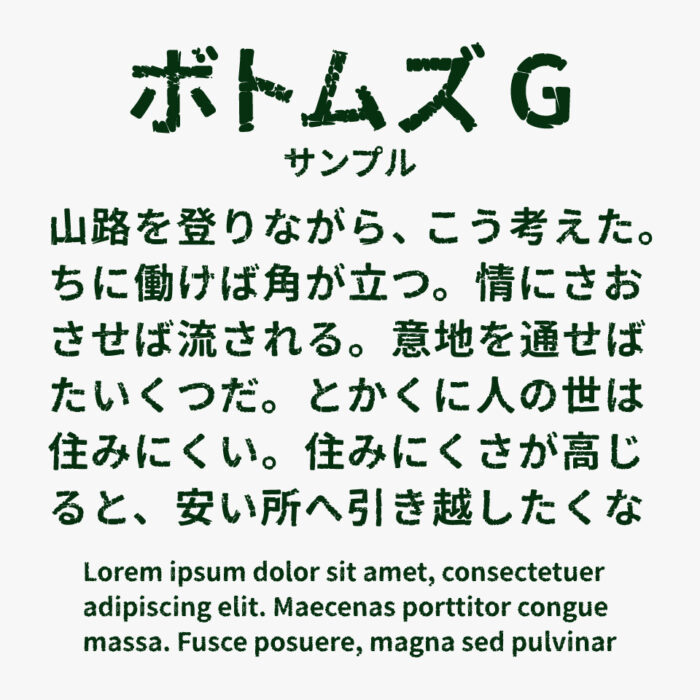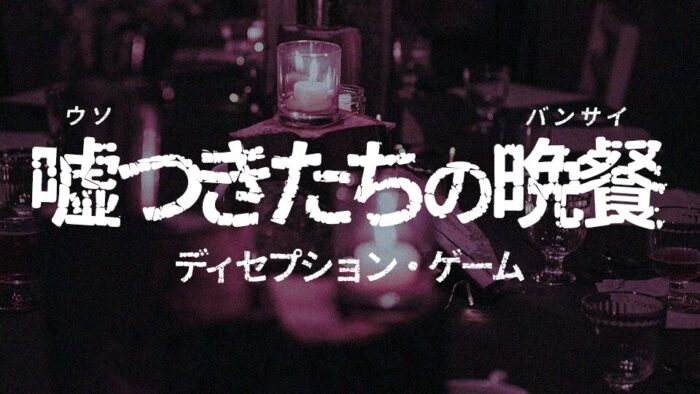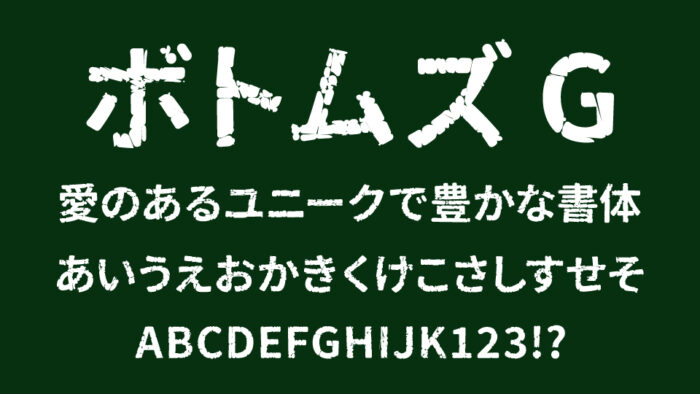
ボトムズGフォントは、明朝体ベースの「ボトムズ」のゴシック体版として調整されたフォントです。
沼底のようなカチカチに干ばつしたような質感がとてもユニークで面白いフォントです。
ミステリー系、サスペンス系、ホラー系のジャンルにぴったりですが、グランジの質感がアウトドアやサバイバル、DIYといったコンテンツにもハマりるフォントです。